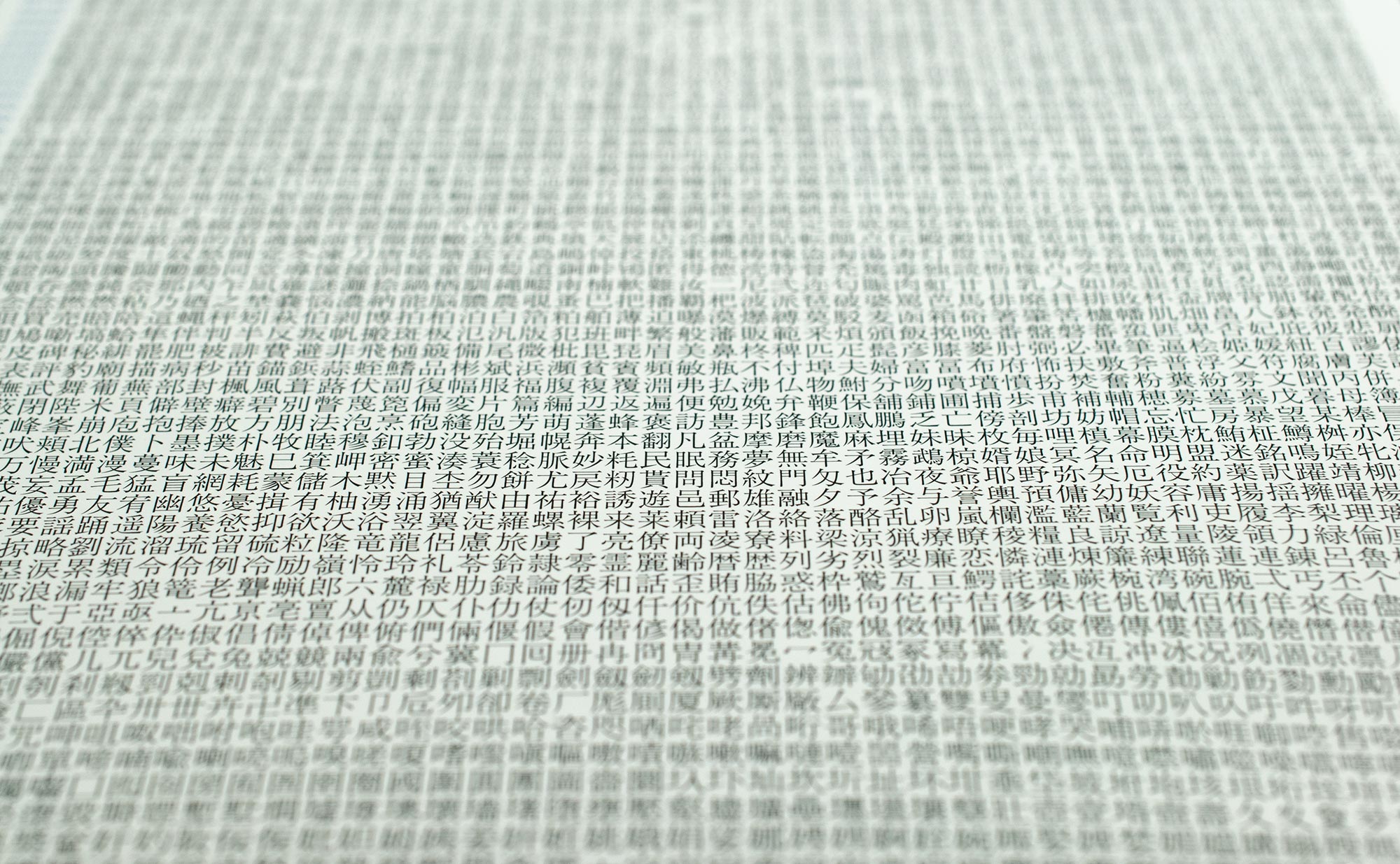
Schriftzeichen und Fonts
Komplexe Kanji, einfache Kana und die Folgen
Das Meer der japanischen Zeichensätze ©2016 Mynavi Publishing Corporation
Die Unmöglichkeit von japanischen Corporate-Fonts
Anders als in den Ländern mit lateinischem Alphabet ist in Japan die Menge der bisher entworfenen Schriftarten aufgrund ihres komplexen Schriftsystems sehr überschaubar. Bis heute habe ich noch nie gehört, dass ein japanischer Corporate-Font exklusiv für ein Unternehmen entworfen worden wäre. Die ersten Unternehmen haben gerade angefangen, zum Teil, nur für die lateinischen Buchstaben und die Ziffern, bestimmte Schriftarten zu verwenden. Anstelle des Wortes »Corporate Design« verwendet man auf den Inseln den Ausdruck »Visual Identity«, und dabei bezieht man sich hauptsächlich auf das Unternehmenslogo und die Anwendung in seinem direkten Umfeld. Von exklusiver Nutzung einer Hausschrift ist nirgends die Rede, weil jeder weiß, was für eine aufwendige Aufgabe es ist, einen kompletten Satz Schriftzeichen für einen japanischen Font zu entwerfen.
Japanische Fonts
Ungefähr drei bis vier Tausend digitalisierte japanische Fonts dürften auf dem japanischen Markt zu erwerben sein. Ein japanischer Font besteht eigentlich zum größten Teil aus chinesischen Schriftzeichen, den Kanji (Kanji-Tabelle mit 6.494 Kanji). Und gerade bei diesen ist es besonders schwierig, etwas Neues zu entwerfen, da es immerhin über 400 Schriftzeichen gibt, die aus mehr als 20 Strichen bestehen (werfen Sie doch einen Blick darauf: hier). Je mehr Striche ein Schriftzeichen hat, umso weniger Weißräume bleiben für die Gestaltung. Das heißt, je komplexer es ist, desto schwieriger ist es auch, ihm eine Form zu geben, die sich deutlich von dem gleichen Schriftzeichen aus einem anderen Font abhebt. Diese Tatsache schreckt die meisten Typedesigner davon ab, sich einer solchen Herausforderung zu stellen.
Vier Kanji in zwei Schriftarten: A1 Mincho (oben) und Gothic MB101.
Das erste und das zweite Kanji wird jeweils in 24, das dritte in 26, das vierte in 29 Schritten geschrieben (v.l.n.r.).
Kana-Zeichen
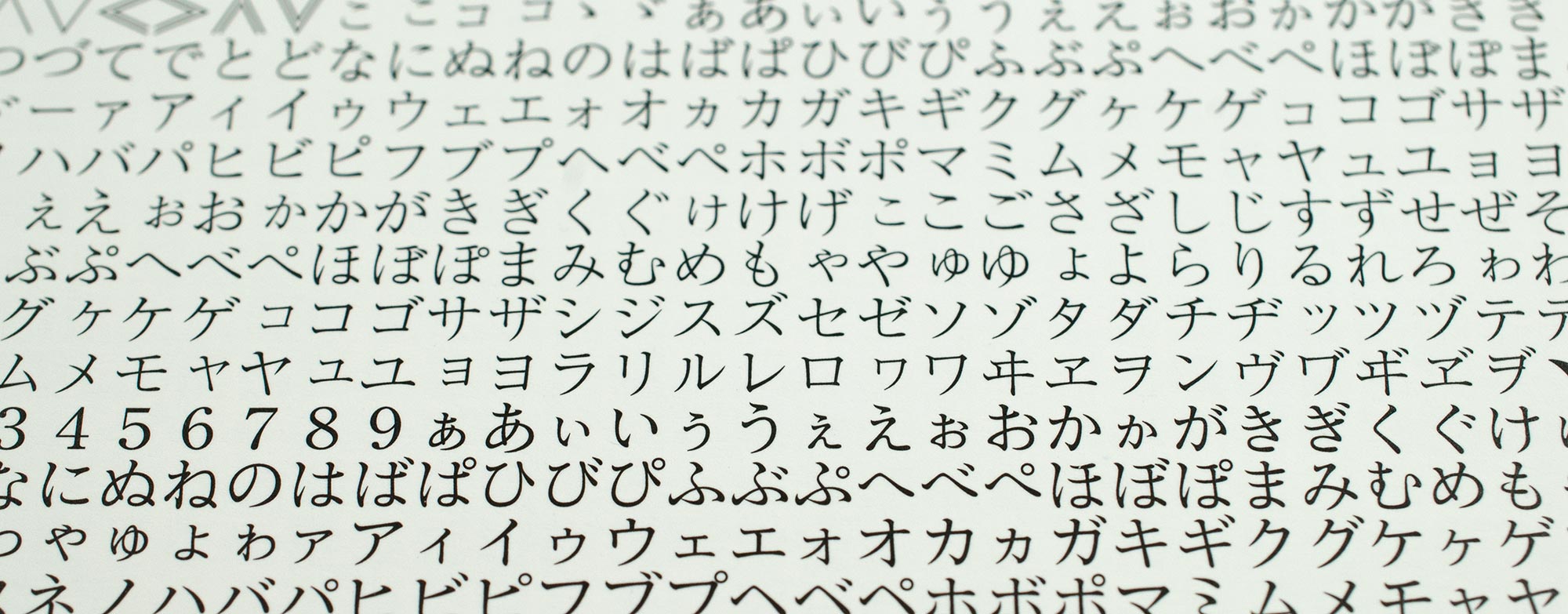
Die Form der japaneigenen Silbenzeichen, Hiragana und Katakana, ist dagegen sehr einfach. Sie bieten also Designern viele Freiräume, auch ist ihre Zahl mit je 46 noch gut überschaubar. Sie machen nur einen verschwindenden Teil eines japanischen Fonts aus, während die Kanji bis zu 90 Prozent des gesamten Platzes in Anspruch nehmen, sind aber entscheidend für das Erscheinungsbild des japanischen Textes, weil 60 bis 70 Prozent mit diesen Kana geschrieben bzw. gesetzt werden. Jedes Kana steht täglich viele Male im Rampenlicht, aber es gibt zahlreiche traurige, seltene Kanji, die zwar entworfen wurden, aber wahrscheinlich nie in ihrem Leben zum Einsatz kommen werden. Aus diesem Grund lohnt sich die Arbeit an den Kana besonders und es gibt in der Tat viele Typedesigner, die auf Kana spezialisiert sind. Möglicherweise gibt es heute schon auf dem japanischen Markt mehr Fonts ohne Kanji (sogenannte »Kana-Fonts«) als mit Kanji.
Hiragana (links) und Katakana aus denselben Schriftarten wie die Kanji oben. Im Gegensatz zu den komplexen Kanji lassen sich Kana viel freier gestalten.
»Gemischte« Fonts
Ein japanischer Font ohne Kanji? Man fragt sich vielleicht, was man denn damit anfangen soll. Ganz einfach: Man setzt ihn mit einem vollständigen buchstäblich zusammen. D.h., die vorhandenen Kana in einem kompletten japanischen Font werden durch andere ersetzt. Dieses »Kompositum« wird nun eine neue »gemischte Schriftdatei« und kann wie jeder normale Font verwendet werden. Mit Japanischen Satzprogrammen wie InDesign, PageMaker und QuarkXPress kann man beliebige »Komposita« im Handumdrehen erstellen und verwalten (am Beispiel von InDesign zeige ich das hier). Diese Praxis gibt es außerhalb Japans wohl nirgends, aber hierdurch genießen japanische Setzer heutzutage eine große Flexibilität bei ihrer Arbeit.
Beispiel:
Ich ersetze die Kana von der Hiragino Kaku Gothic, der Standardschrift in Mac OS X, durch die Kana von »Tsukiji«, einem der bedeutendsten Kana-Fonts von Shintaro Ajioka.
Hiragino Kaku Gothic. Ihre Kana (oben) und das Erscheinungsbild eines Absatzes:
Kanji unverändert, Kana ausgetauscht. So lässt sich der Gesamteindruck japanischer Texte wirkungsvoll ändern.
Im obigen Beispiel wurden nur zwei verschiedene Fonts gemischt. Dabei ist die Zahl der einsetzbaren Fonts nicht beschränkt. Man kann zum Beispiel für lateinische Buchstaben einen anderen Font, für Ziffern einen weiteren nutzen usw. Es ist sogar möglich, nur für ein einziges Zeichen bzw. einen Buchstaben eine bestimmte Schriftart zu verwenden.
Zum komplexen Thema »lateinische Buchstaben im japanischen Text« erfahren Sie mehr unter »Lateinische Buchstaben«.
Die Idee, das japanische Schriftbild nur durch das Auswechseln der Kana zu verändern, ist relativ neu. Japanischen Grafikdesignern wurde die große Bedeutung dieser skurrilen Idee erst so richtig klar, als der Kalligraf Shintaro Ajioka in den 80er Jahren seine bahnbrechende Arbeit präsentierte, die als der Grundstein für die heutige Entwicklung der japanischen Schriftgestaltung gilt.
Auf der Seite »Japanische Kana-Fonts« stelle ich Ihnen seine Schriften ausführlich vor.
Kanji, Kana und ihre Lesbarkeit
Kanji und Kana unterscheiden sich nicht nur in ihrem Äußeren, sie haben auch klar getrennte Funktionen im geschriebenen Text und spiegeln seine grammatische Struktur wider, wodurch das Erfassen des inhaltlichen Zusammenhangs optisch quasi doppelt erleichtert wird. Mit anderen Worten, das Erscheinungsbild von Kanji und Kana sollte sich nicht zu sehr ähneln, sonst sinkt die Lesbarkeit. Aus diesem Grund sind Kana eines gut lesbaren japanischen Fonts prinzipiell kleiner und individueller gezeichnet als Kanji, und diese Tendenz ist bei Mincho-Schriften deutlicher zu beobachten als bei Gothic-Schriften.
Eine Mincho-Schrift hat in der japanischen Typografie eine ähnliche Stellung wie eine Antiqua in der europäischen Typografie. Bei Fließtexten ist eine (gute) Mincho-Schrift besser lesbar als eine Gothic-Schrift, die nach ihrem Charakter einer serifenlosen Linear-Antiqua entspricht. Mincho-Schriften haben ein interessantes Merkmal, das jedoch nicht jedem sofort auffällt. Erst bei genauerem Betrachten erkennt man, dass Kanji und Kana einer Mincho-Schrift eigentlich nicht viel gemein haben.
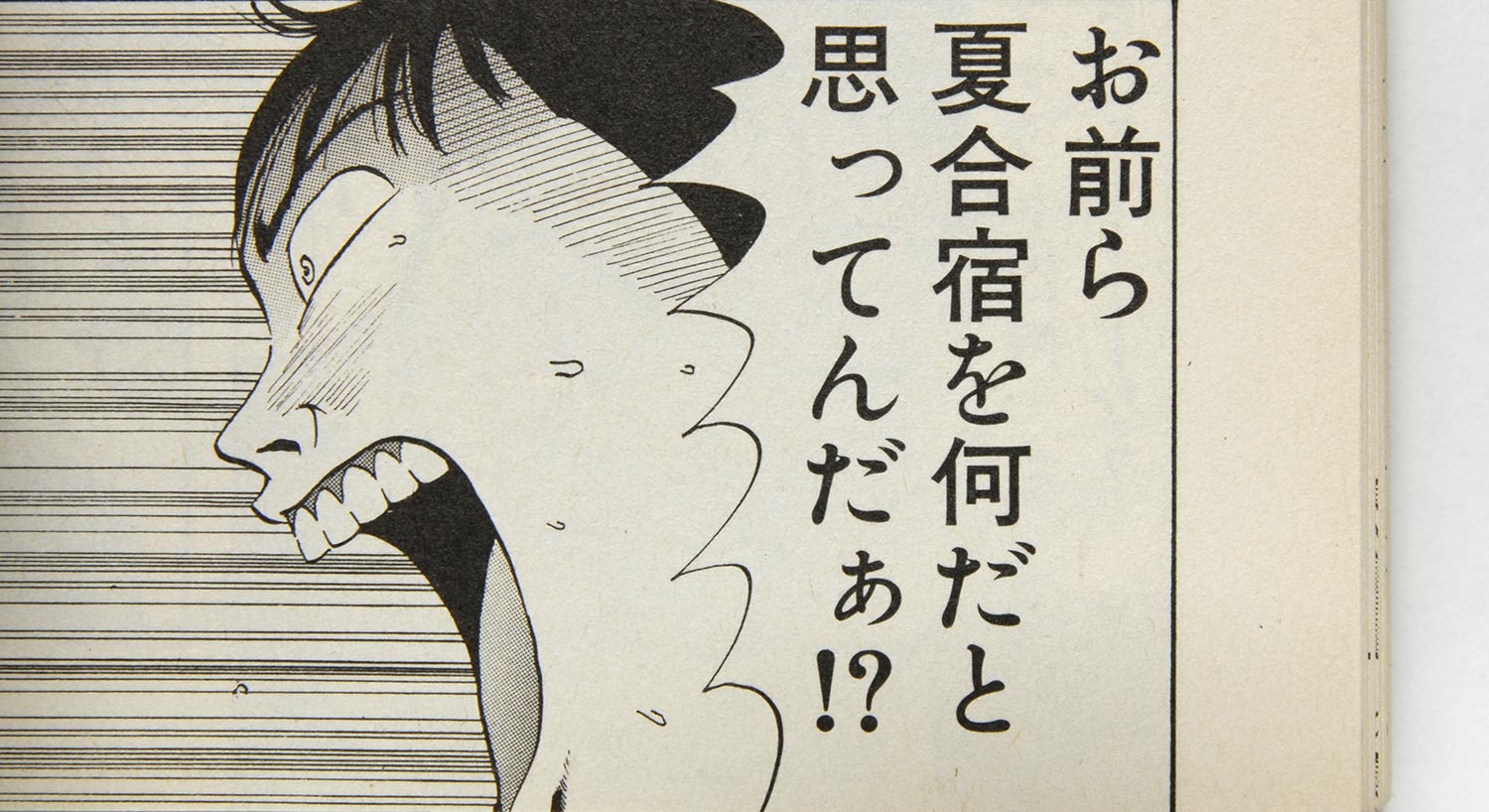
Altbewährte Tradition: Kanji in Gothic, Kana in Mincho gesetzt. Für Dialogtext in Manga werden seit etwa den 1950er Jahren diese zwei Schriftarten gemischt, was aus europäischer Sicht einem Zusammenfügen von einer Grotesk und einer Antiqua gleich käme. Diese damals innovative Mischung ist so gelungen, dass viele Japaner überhaupt nicht wahrnehmen, dass sie eigentlich zwei Schriftarten lesen.